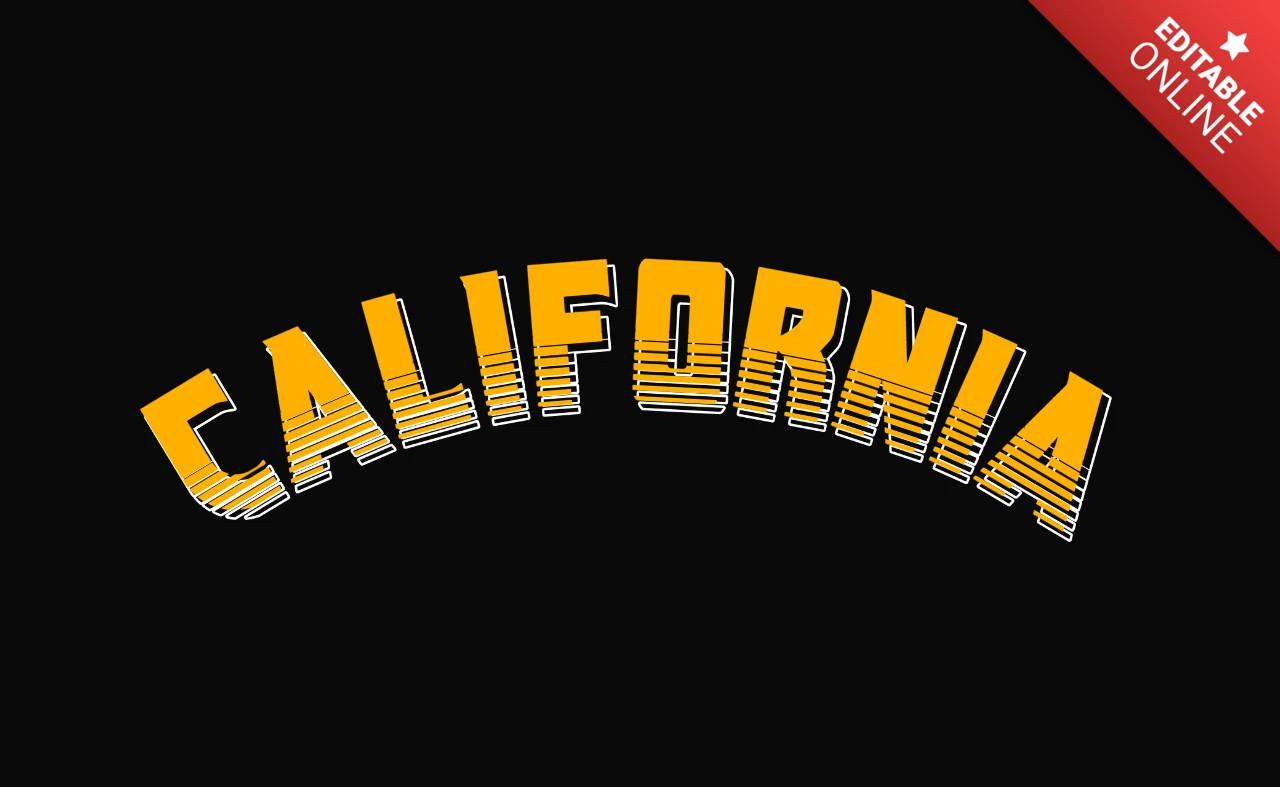
Modèle de t-shirt avec typographie urbaine californienne
Éditer dans Design Studio Télécharger en JPGCréez de superbes designs de t-shirts avec notre modèle vintage sur le thème de la Californie dans notre éditeur de design en ligne. Personnalisez facilement la typographie et les éléments urbains pour un design de t-shirt unique.